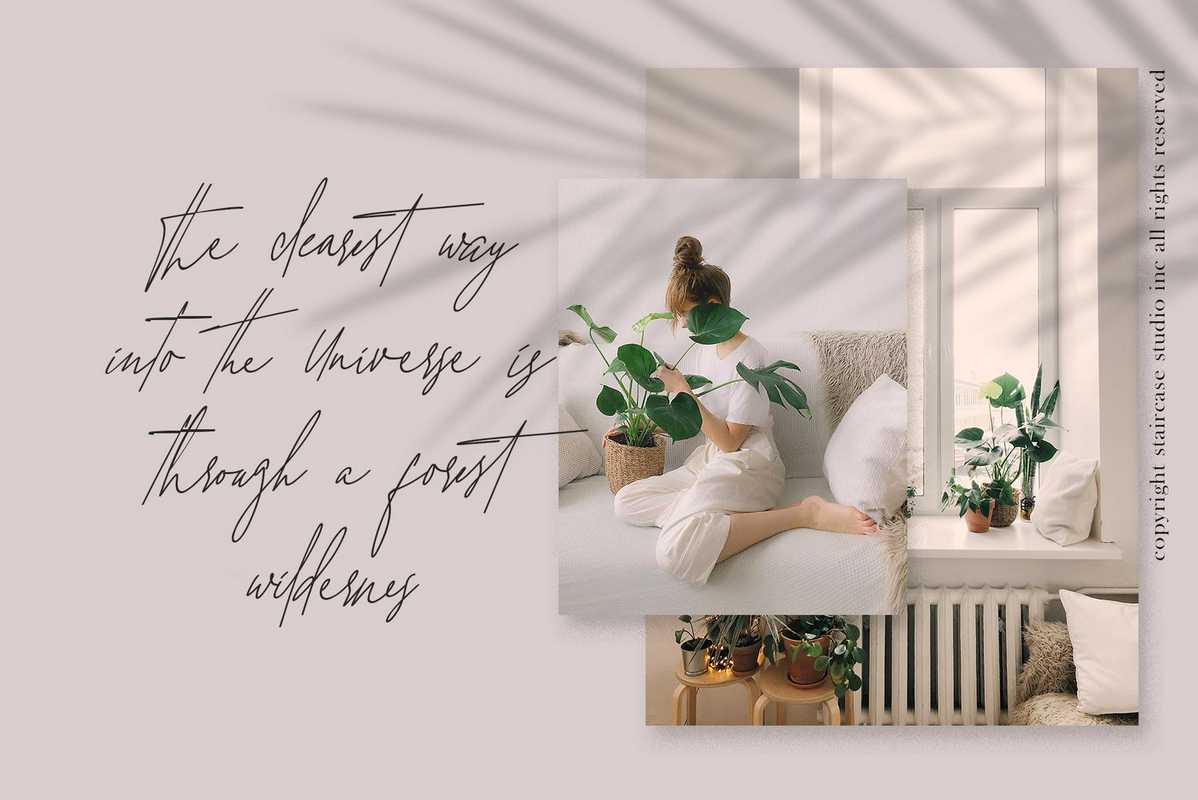
Christina Callista With Handrittentype字体。适合您项目的文字和数字集合非常适合于标识、品牌设计、标志设计、数字刻字艺术、T恤/服装、海报、杂志、标志、广告设计和任何设计需求。Christina Callista With Handrittentype字体。适合您项目的文字和数字集合非常适合于标识,品牌设计、标志设计、数字文字艺术、T恤/服装、海报、杂志、标志、广告设计和任何设计需求。